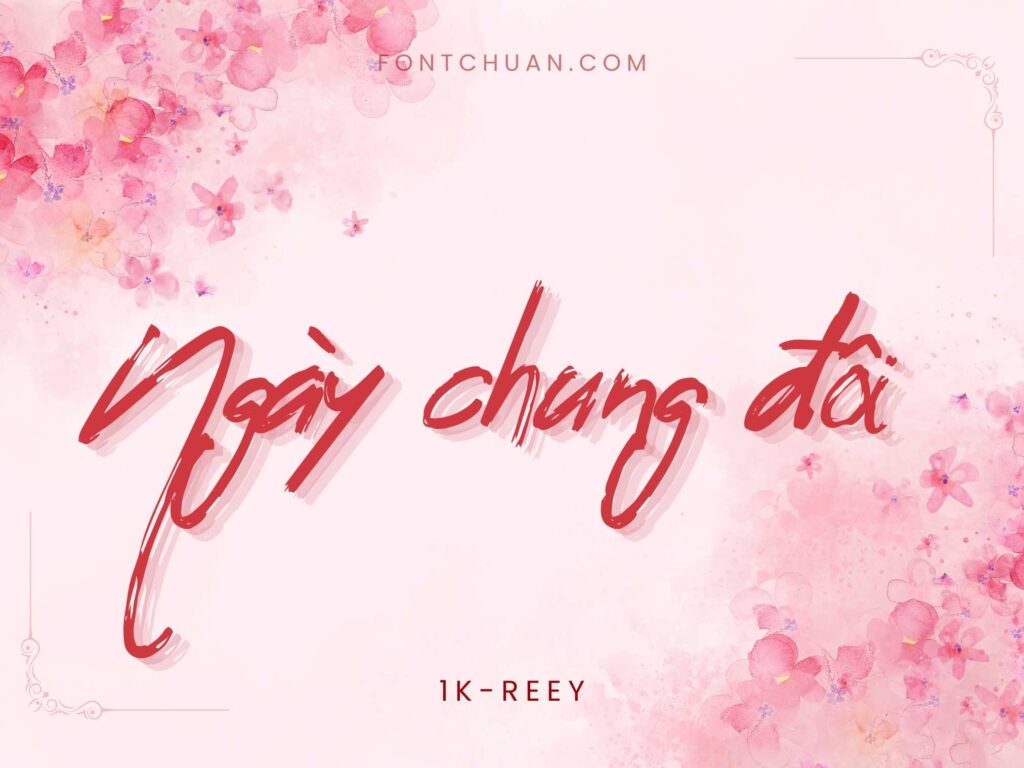
Font 1K Reey Việt Hóa
Tác giả Font: Koen Van Der Bliek
1K-Reey là phiên bản Việt hóa của phông chữ Reey, được thiết kế bởi Koen van der Bliek. Đây là một phông chữ viết tay với phong cách hiện đại, mang lại cảm giác tự nhiên và thân thiện cho các thiết kế. Phiên bản đầu tiên được phát hành vào năm 2017. Font này đã được FontTiengViet Việt hóa, hỗ trợ đầy đủ các ký tự tiếng Việt, giúp người dùng dễ dàng áp dụng trong các dự án thiết kế đa dạng. Ngoài tiếng Việt, font còn hỗ trợ hơn 12 ngôn ngữ khác, bao gồm tiếng Anh, Đức, Pháp, Ý và Tây Ban Nha. Phông chữ này được thành viên Font Chuẩn sưu tầm và đăng tải nhằm phục vụ nhu cầu sáng tạo phong phú.
Với thiết kế viết tay hiện đại và thân thiện, 1K-Reey phù hợp cho các ứng dụng như thiệp mời, tiêu đề, logo và các ấn phẩm in ấn cần sự cá nhân hóa. Các ký tự có độ cao x trung bình, tạo nên sự tinh tế và mềm mại trong văn bản. Font cũng bao gồm các ligatures, giúp tăng tính liên kết giữa các chữ cái, tạo nên sự mượt mà trong thiết kế. Trong lĩnh vực sự kiện, phông chữ này có thể được sử dụng trong các dịp như thiệp cưới, lễ hội và sinh nhật. Ngoài ra, 1K-Reey cũng thích hợp cho các ngành nghề như quảng cáo, giáo dục và công nghệ.
Bên cạnh đó, 1K-Reey còn có thể được sử dụng như một Font chữ bất động sản trong các dự án truyền thông thương hiệu, thiết kế biển bảng, brochure hay logo cho doanh nghiệp nhà đất. Sự mềm mại và tự nhiên của font giúp cân bằng giữa tính hiện đại và cảm xúc, tạo ấn tượng thân thiện, đáng tin cậy cho khách hàng.